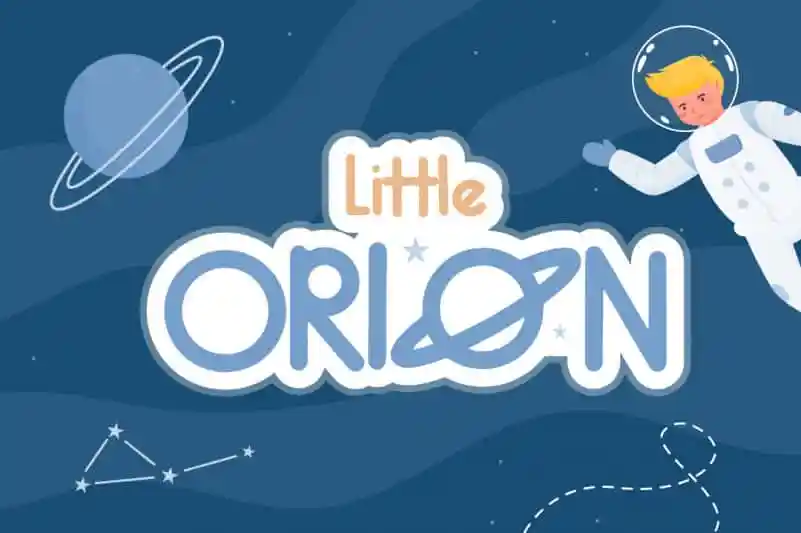
Little Orion Handwritten Font – Download Grátis
A Little Orion Handwritten Font é uma delícia para os olhos, com suas letras delicadas e suavemente amigáveis. Este estilo retrô e aconchegante torna cada projeto escolar ou infantil um pouco mais especial e encantador. Imagine crianças sorridentes usando esta fonte em seus trabalhos de casa, dando vida aos desenhos animados favoritos com uma pitada de originalidade irresistível. Ou imagine o gosto refrescante da piscina de verão impresso na escola. Little Orion Handwritten Font não apenas enriquece a aparência de seu projeto, mas também adiciona um toque especial e pessoal que certamente chamará a atenção das crianças. Seja para desenhos animados ou escritas poéticas, esta fonte é uma ótima escolha para qualquer criança apaixonada por letras e cores vibrantes.